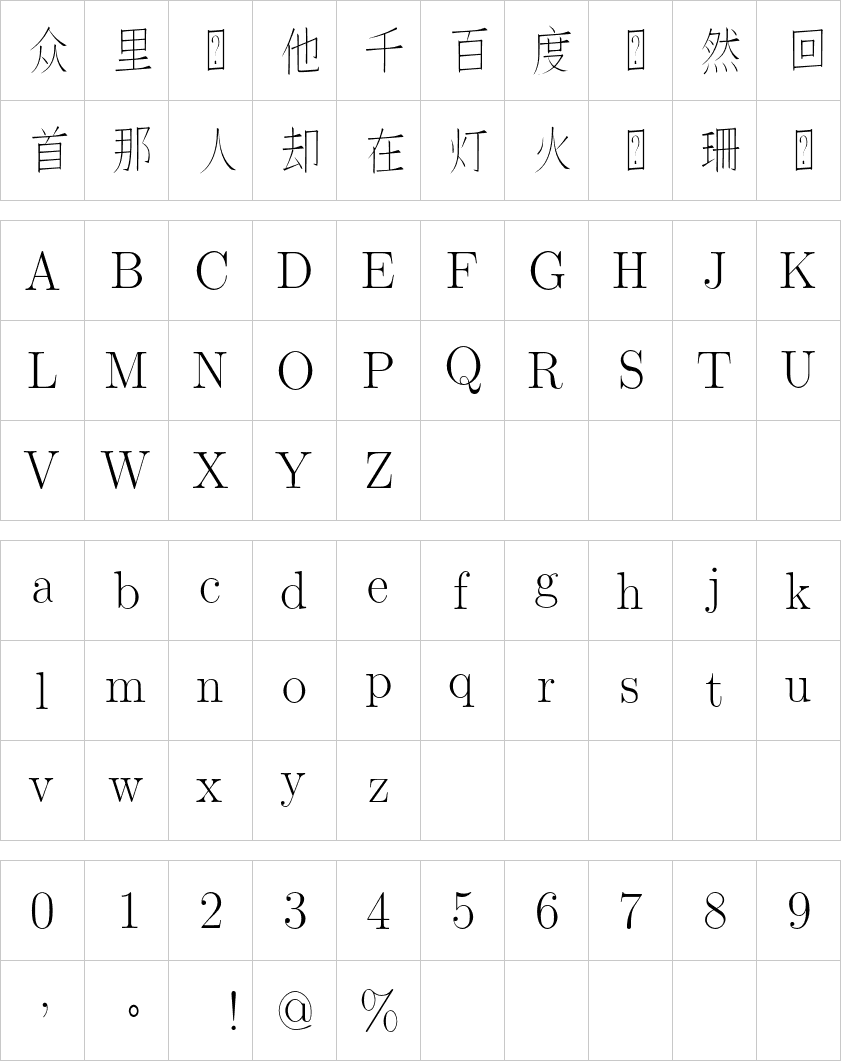
HZ 宋朝
HZ 宋朝字体在线预览效果
HZ 宋朝字符映射图
这是一个免费的OpenType cid的日文字体,来自字形维基(GlyphWiki)的CJK数据,有5个字重。
拉丁文、希腊文和西里尔字母并非源自字形维基(GlyphWiki),而是源自Computer Modern Unicode,因为GlyphWiki的Kage引擎是为中文字符设计的。
一些符号来自M+字体和GL Antique字体。
This is a free/libre OpenType CID-keyed Japanese font derived from GlyphWiki’s CJK data, with weight variations.
Latin, Greek and Cyrillic glyphs are not derived from GlyphWiki but from Computer Modern Unicode because GlyphWiki’s Kage engine is intended for Chinese characters and not good at LGC.
Some symbols are from M+ fonts and GL Antique font.